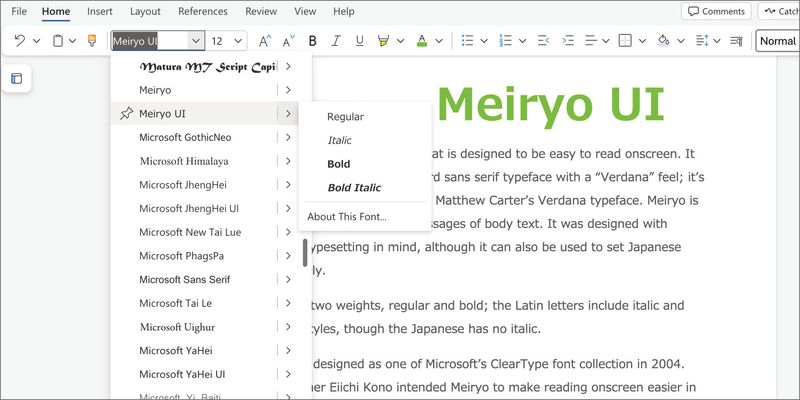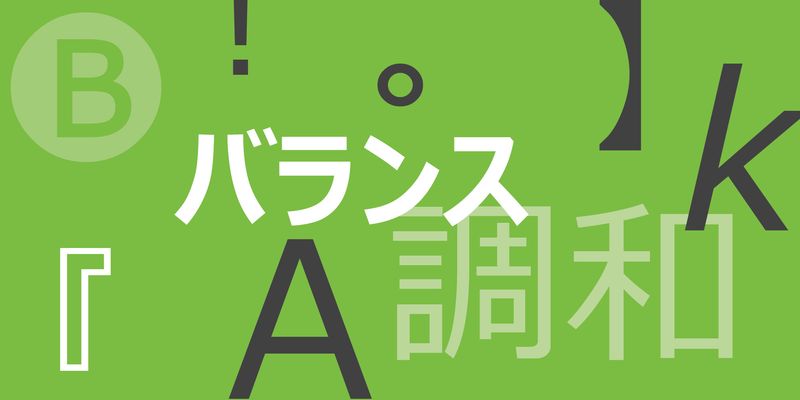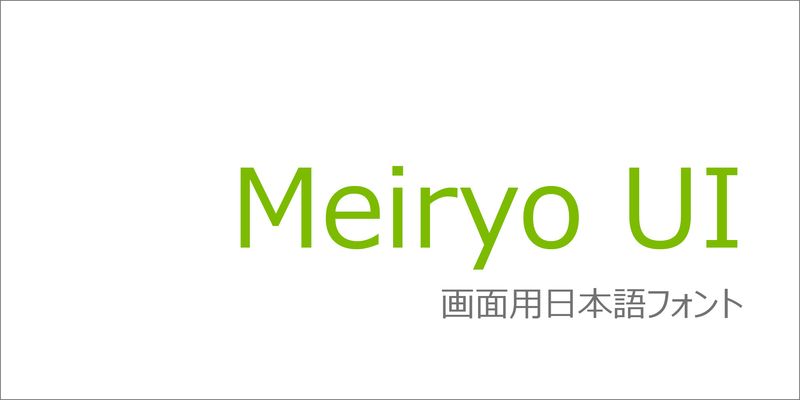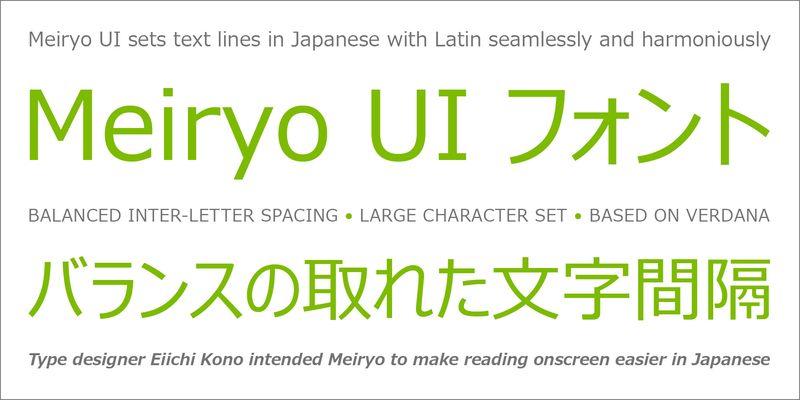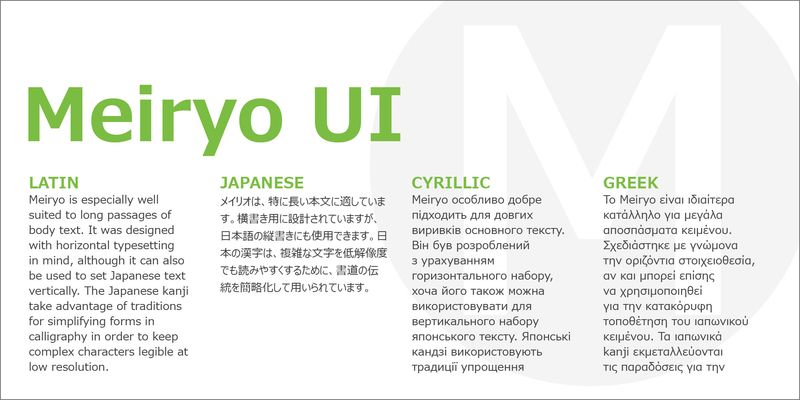
Meiryo는 화면에서 읽기 쉽게 디자인된 일본어 서체입니다. “Verdana” 느낌이 나는 깔끔하고 단순하며 직관적인 산세리프체입니다. 이 서체의 라틴 문자는 사실상 Matthew Carter의 Verdana 서체를 기반으로 합니다. Meiryo는 특히 긴 본문 텍스트에 적합합니다. 수평 조판을 염두에 두고 디자인되었지만 일본어 텍스트를 세로로 조판하는 데에도 사용할 수 있습니다.
Meiryo는 두 가지 두께인 Regular와 Bold로 제공됩니다. 라틴 문자에는 이탤릭체와 볼드 이탤릭 스타일이 있지만 일본어에는 이탤릭체가 지원되지 않습니다.
Meiryo는 2004년 Microsoft의 ClearType 글꼴 컬렉션 중 하나로 디자인되었습니다. 타이프 디자이너 Eiichi Kono는 일본어가 화면에서 더 잘 읽히도록 Meiryo를 설계했습니다. 일본어 간지는 서예 전통에서 글자 형태를 단순화해 온 방식을 활용하여 저해상도 환경에서도 복잡한 글자가 잘 보이도록 했습니다. Meiryo의 라틴어, 그리스어 및 키릴 문자는 서구 언어 화면용 글꼴인 Verdana를 디자인했던 Matthew Carter가 담당했습니다.